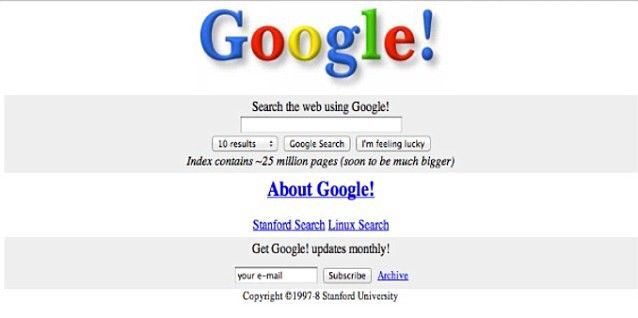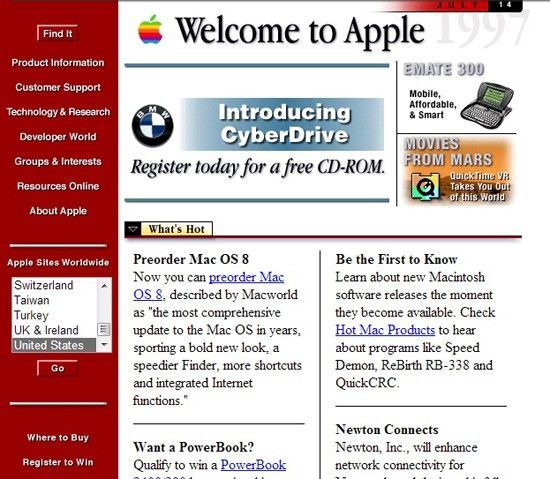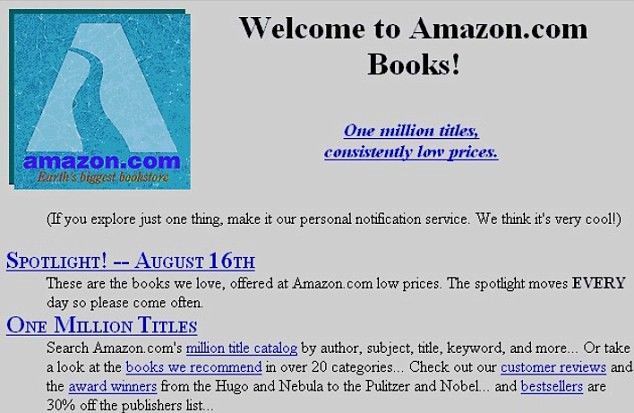
Шрифт New York от Apple с засечками: что это значит для веб-дизайна?
Итак, Apple недавно выпустили шрифт с засечками. Так же, как и все шрифты Сьюзен Каре, такие как Сан-Франциско, Чикаго, который был официальной яблочной гарнитурой вплоть до первых дней выпуска iPod, эта новая гарнитура также названа в честь города: Нью-Йорк. Теперь он доступен для скачивания с официального сайта Apple вместе с текущим по умолчанию и любимым шрифтом без засечек: Сан-Франциско.
Таким образом, этот шрифт снова возвращается в моду, становится лидером в новых трендах, которые неизбежно станут модными среди крупных технологий и в конечном итоге станут новой нормой. Итак, что этот выпуск говорит нам о состоянии интернет-типографики, и есть ли что-то еще, что мы можем извлечь из этого «не столь удивительного» выпуска? Спойлер: есть, и это на самом деле супер захватывающе ?!
Apple не первый, кто возвращается к засечкам
Прежде чем мы начнем, я считаю необходимым отметить, что Apple не первая компания, которая возвращается к Serifs. Google уже довольно давно использует шрифты с засечками. В 2013 году, компания выпустила Roboto Slab, и она использовала данную гарнитуру здесь и на других страницах своих продуктов, таких как Sheets и Jamboard. Но эти страницы давно не обновлялись. IBM также не забыла о засечках в своем новом языке дизайна. Вы действительно можете увидеть, что они уделили много внимания и вложили кучу сил в IBM Plex Serif. Но примеров мало. Сказать, что Сан-Сериф является королем в наше время, было бы преуменьшением.
Технические стартапы и небольшие компании ничем не отличаются. Хотя многие используют современные шрифты, а иногда и фирменные шрифты, все придерживаются использования шрифтов без засечек. Взгляните, например, на WeWork. Несмотря на то, что они используют шрифт с засечками в логотипе, у них на сайте нет ни одного символа с засечками. Помимо журналов, таких как Wired или The Guardian, и таких модных брендов, как Vogue, засечки, похоже, забыты в любом крупном бренде.
Почему все используют шрифты без засечек?
Хотите верьте, хотите нет, было время, когда интернет был полон гарнитур с засечками, около двадцати лет назад. В том числе и Apple, Google и Amazon использовали serif на своих домашних страницах. Microsoft, использовала Times New Roman в качестве шрифта по умолчанию в Word вплоть до 2007 года, до выпуска Calibri.
• Amazon (1994)
• Apple (1997)
• Google (1998)
Так почему же все предпочитают шрифты без засечек? Оказывается, это больше связано с историей типографики и ранних цифровых дисплеев.
Исторические причины:
Серифы можно проследить до исторического использования каллиграфических инструментов, таких как ручка броадниб и монолайн, для создания буквенных форм. Вы определенно можете увидеть, как использование таких инструментов, в отличие от современной ручки (шариковая ручка) с сухими чернилами, может повлиять на ваше письмо (подробнее об этом читайте в Keith Tam). Это сделало такие шрифты нормой для ранней типографики и печати, потому что они не создают особых проблем.
Ручка броадниб (широкое перо)
Однако в более ранних технологиях отображения отсутствовала достаточная плотность для правильного отображения засечек, как при печати. В результате шрифты с засечками стали более размытыми с артефактами сглаживания, поскольку они более плотные. Гарнитуры без засечек выглядели более четкими, следовательно, обрели большую популярность в веб-дизайне.
Например, оригинальный iMac, продаваемый с 1998 по 2003 год, имел плотность экрана 83ppi (768 x 1024px на 15 "экране). С непрофессиональной точки зрения, это означает, что с нормального расстояния вы явно сможете различить отдельные пиксели, учитывая правильный контраст. Этого недостаточно для комфортного использования засечек в мелком шрифте.
В настоящее время 15-дюймовый MacBook Pro имеет разрешение 221ppi, а iPhone XS Max - 458ppi. Это означает, что если бы они добавили больше пикселей на эти экраны, вы бы не смогли заметить разницу, как продемонстрировано в видео по техническим советам Linus. Таким образом, плотность экрана является наименьшей из проблем, когда дело доходит до выбора шрифта.
Поэтому, несмотря на то, что засечки начали использовать в эпоху цифровых технологий, разрешение экрана стало важной причиной того, что san serifs быстро завоевали популярность и приобрели «цифровой» вид.
Но как бы нам ни хотелось рационализировать выбор шрифта, прибегая к аргументам, таким как разрешение экрана или мифам, таким как странное убеждение, что засечки вредны для SEO или что они дают лучшую читаемость, факт в том, что выбор зависит от контента веб-сайта, и это в значительной степени эстетический выбор каждого в большинстве случаев.
Все вскоре изменится, и Apple собирается быть первыми
Первый телефон с сенсорным экраном уже существовал, когда Apple представила iPhone. Тонкие ноутбуки были также до MacBook Air и Full были до AirPods. Видите ли, дело в том, что мы не рассчитываем, что верно, а что нет. Мы проектируем в основном то, что люди посчитают верным. В настоящее время современный внешний вид - это дизайн без засечек, очень дышащий, с собственными иллюстрациями. необходимо сильно потрудиться, чтобы вникнуть в текущую веб-культуру.
Итак, с учетом сказанного, я думаю, все, что осталось сказать: Добро пожаловать, Нью-Йорк!